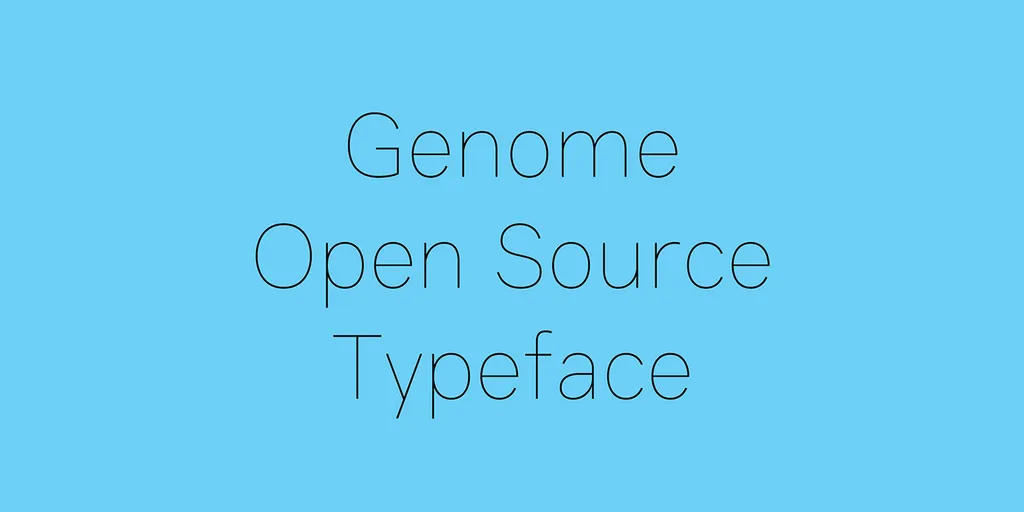
Genome Font
A ‘Genome Font’ é uma escolha perfeita para a categoria de fuentes sans serif. Seu design limpo e proporcional se destaca especialmente para uso em formatos digitais, tornando-a ideal para aumentar a leitura confortável em telas. Suporte à futura evolução da ‘Genome Font’ é sempre bem-vindo, uma vez que suas proporções garantem um ótimo visual tanto online quanto offline. Esta fonte promete melhorar não apenas a aparência do seu projeto, mas também sua legibilidade e engajamento, tornando-a uma fonte recomendada para qualquer tipo de projeto gráfico moderno.